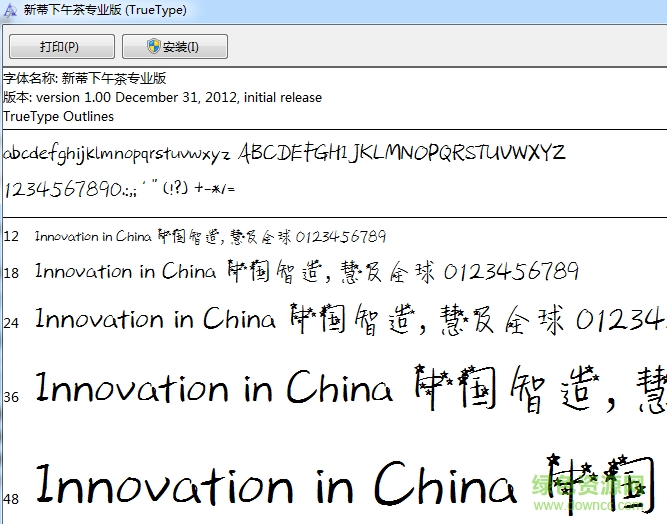
繁星空點(diǎn)點(diǎn)個(gè)性字體
繁星空點(diǎn)點(diǎn)字體是一款極具個(gè)性的中文字體,該字體中偶爾穿插的星星,給字體賦予了新的生命力,讓整個(gè)字活了起來,有需要這款字體的朋友就趕快來綠色資源網(wǎng)下載使用!
繁星空點(diǎn)點(diǎn)字體